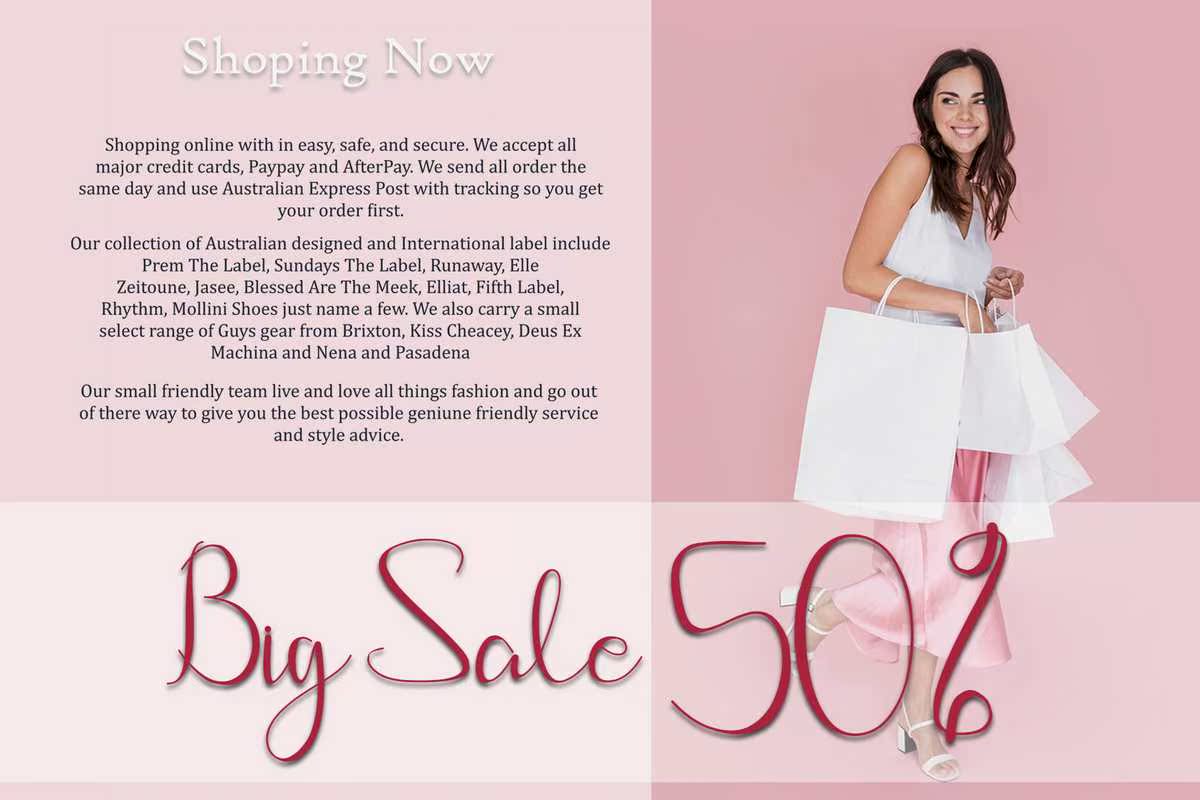
Hayatti是一种现代书写字体。这种字体可以让你的书写和品牌优雅美丽。Hayatti擅长于独特的品牌、照片覆盖、水印、贺卡、海报、名片、邀请函、婚礼、摄影、时尚、服装、信件、文具等。a-z,备选字体(a-z)和连字包括:你可以使用你的logo或ameacustom、手写字体。Hayatti是现代和手写字体。这种字体可以使你的书写和品牌优雅或美观。Hayatti擅长于独特品牌、照片覆盖、水印、贺卡、海报、名片、请柬、婚礼、摄影、时尚、服装、信件、文具、,等等。一系列的水洗(a-z)、交替(a-z)和连字都包括在内,因此您可以使用您的标识或手写体、手写体。